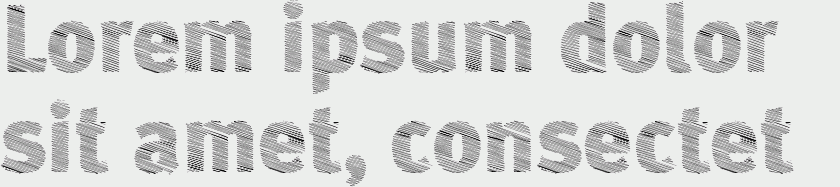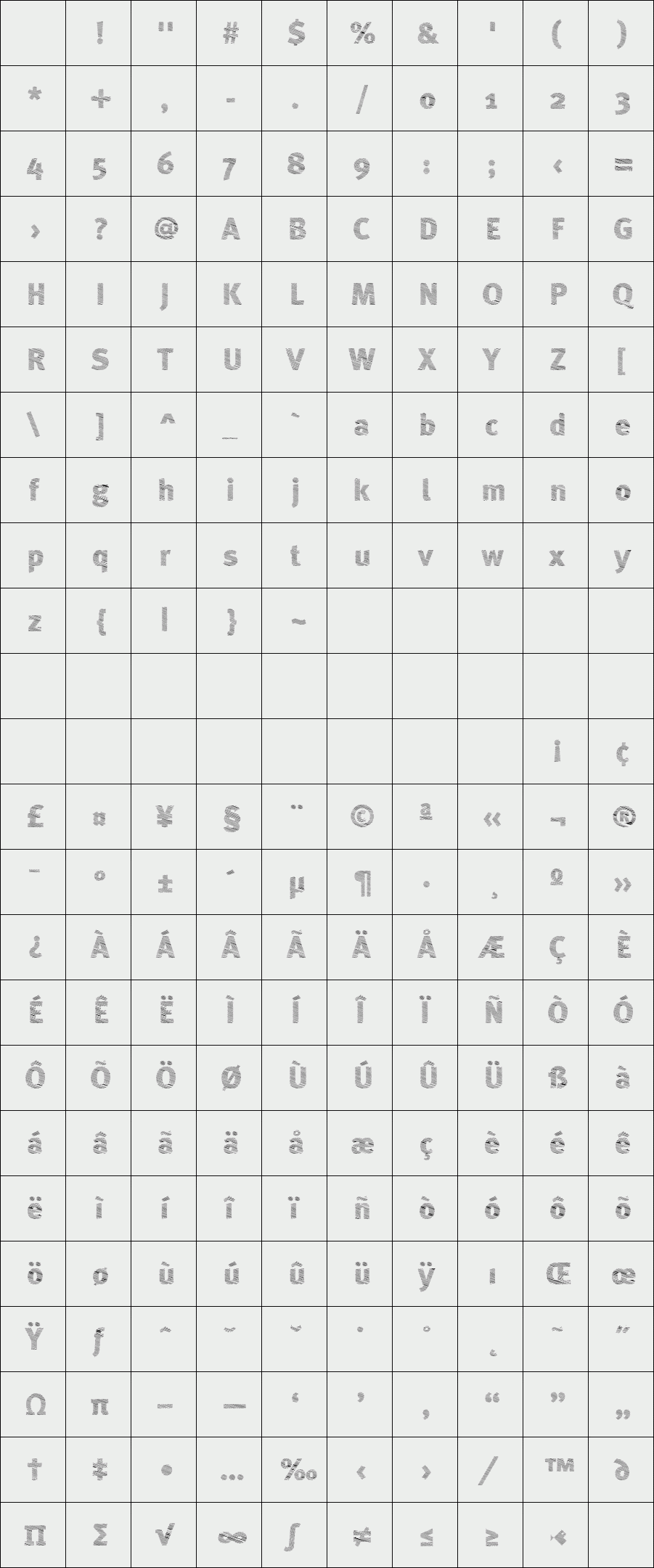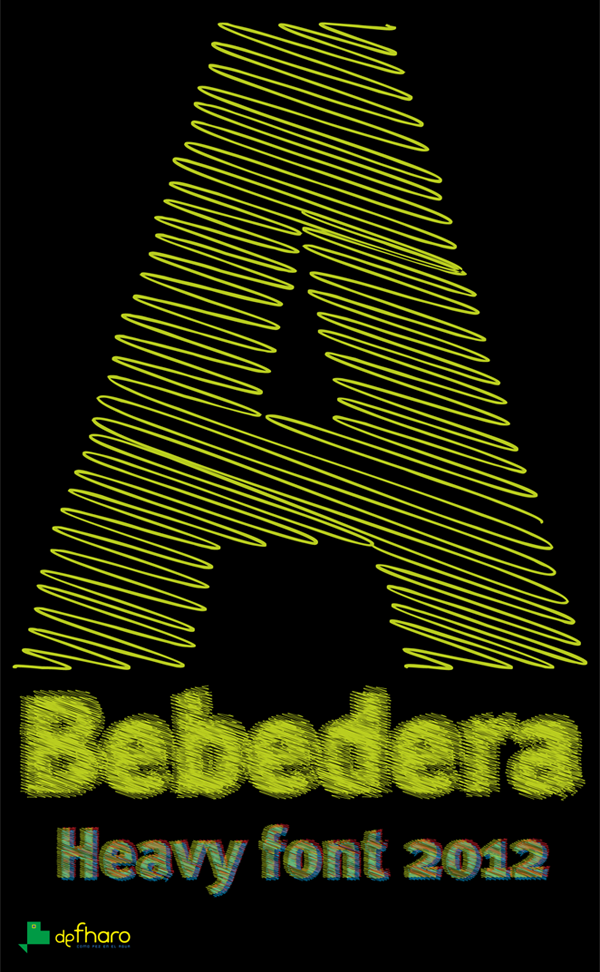
A Bebedera
“A bebedera” – esta frase portuguesa viene a significar “la borrachera“, le he puesto el nombre a la tipografía por la cantidad de curvas que tiene cada glifo…(el vaiven del borracho, y el mareo que me he cogido haciéndola:), también como homenaje a Brasil, donde viví, disfruté y aprendí tanto.